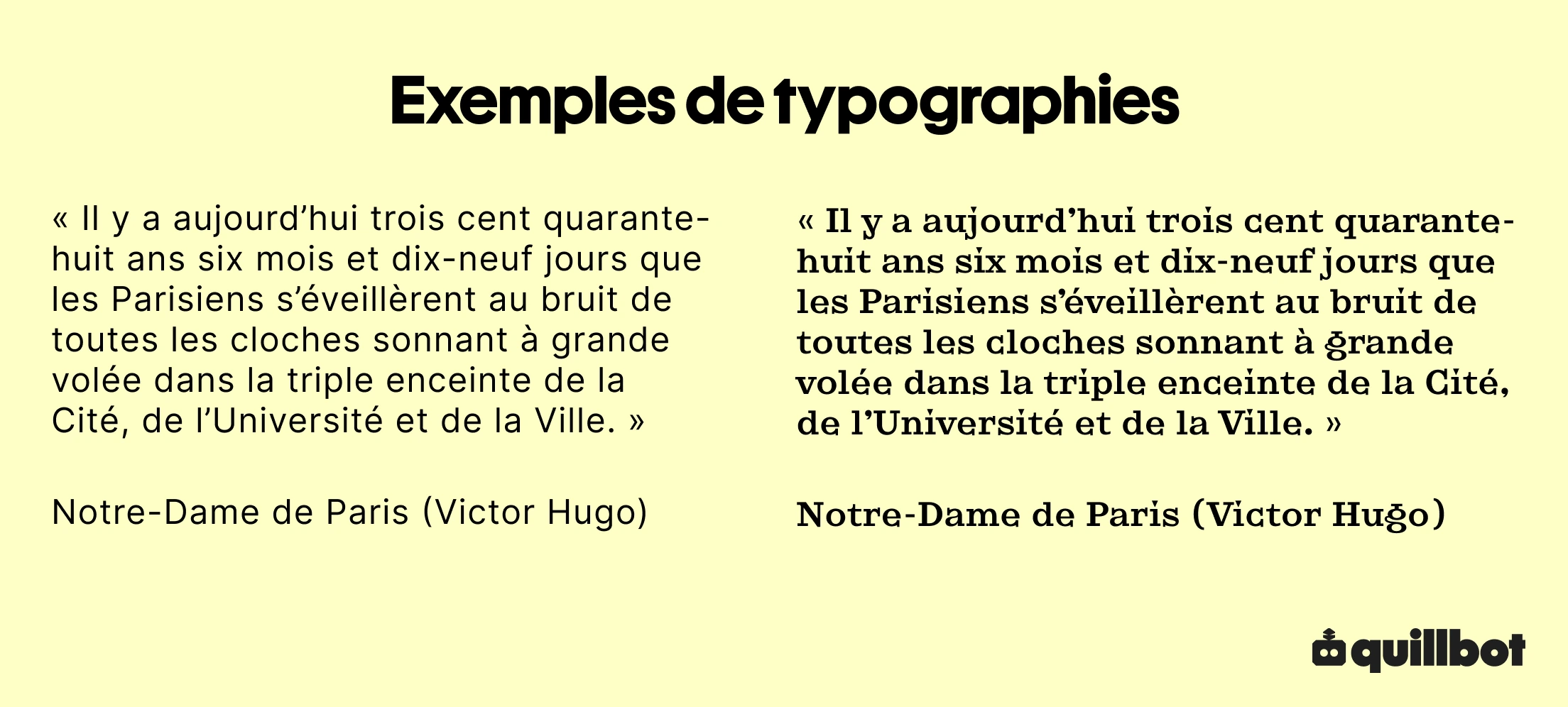
Choisir la bonne typographie | Explications
La typographie pare les lettres d’atours physiques et agence le texte selon une structure canonique. Elle est la clé de voûte d’un esthétisme textuel formel.
Lorsqu’elle est inadaptée, le texte perd bien plus que le sens du message ou la clarté du propos : il perd en crédibilité, et ce, avant même d’être lu.
Primordial, le choix d’une typographie qui captive le public relève d’une cohérence visuelle, qui, au-delà de l’esthétisme, aguiche l’œil du lecteur et séduit l’audience.
Choix typographique : la forme
Par sa forme, sa taille et sa couleur, une police typographique revêt chaque caractère d’un costume spécifique. Loin d’être anodine, cette apparence donne au lecteur une première impression du texte.
Toute personnelle et subjective qu’elle soit, cette première impression est une construction sociale. Les formes et les couleurs transmettent une émotion basée sur un héritage culturel partagé.
La typographie donne le ton d’un texte au premier coup d’œil parce que certaines structures influencent grandement notre jugement.
Bonne typographie
Les polices à empattements
L’empattement (ou serif) d’un caractère correspond à la petite extension à la tête ou au pied des lettres.
Les polices à empattements (comme Times New Roman, Garamond ou Baskerville) facilitent la lecture, mais transmettent également des valeurs d’autorité et de respectabilité.
De manière générale, les lignes droites et les angles de ces polices évoquent l’efficacité, la stabilité et tous les honneurs qui entourent une réputation bien établie.
Du document juridique à l’article universitaire, ces polices angulaires sont privilégiées par la presse traditionnelle et le monde de l’édition pour leur référence visuelle à l’imprimerie classique.
Bon à savoir…
La taille, la forme et l’aspect d’un caractère induisent également sa perception.
Plus le corps du caractère est gros et plus le texte est lisible, ce qui évoque la franchise, mais peut aussi se transformer en défaut : un lecteur âgé se sentira considéré, tandis qu’un lecteur plus jeune s’estimera infantilisé.
Le gras est un artifice typographique majeur, car il attire l’attention sur une information importante. Son abus brouille toutefois la hiérarchisation de l’information.
Au-delà de leur fonction, des traits épais ou fins expriment des notions différentes : la puissance ou la sophistication. L’italique, comme le gras, nécessite une utilisation parcimonieuse et équilibrée en fonction du contenu et de la structure du texte.
Le crénage d’un texte participe également de cette première impression. Un texte très aéré offre immédiatement une impression de calme et de sérénité, alors que des caractères trop resserrés affichent une forte densité, synonyme de tension.
Les polices sans empattements
Les polices sans empattement (ou sans-serif) sont dépouillées et minimalistes. Héritées de la révolution industrielle et liées au courant du modernisme, ces polices (Helvetica ou Futura) éliminent le superflu pour se concentrer uniquement sur la fonction du caractère.
Débarrassées de leurs fioritures, elles témoignent d’une transparence et d’une honnêteté qui écartent toute euphémisation ou infantilisation du message.
Cet aspect direct et sans détour réside également dans le contraste entre l’aspect des caractères. Tandis qu’une police droite exprime la neutralité, l’italique suggère le mouvement et l’urgence ; le gras ralentit la lecture et impose son poids.
Largement plébiscitées sur le web, ces polices font partie de toute communication numérique qui se veut innovante, moderne et tournée vers l’avenir.
Les polices manuscrites
Les polices manuscrites (ou scriptes) imitent l’écriture cursive, celle produite lorsqu’on écrit à la main. Parce qu’elles évoquent l’humain, elles font référence à sa créativité et à son authenticité.
Les courbes et les cercles que produisent les pleins et les déliés d’une plume chargée d’encre sont le gage d’une fabrication artisanale, unique et personnalisée.
Ces polices affichent également une certaine élégance à condition qu’elles ne nuisent pas à la lisibilité des caractères. Symbole de douceur, une typographie arrondie (Comfortaa ou VAG Rounded) doit rester non seulement facile à déchiffrer, mais surtout d’une lecture rapide et aisée.
De fait, la nostalgie que ces polices évoquent permet d’établir un véritable lien de proximité entre le texte et son lecteur.
Choix typographique : le public
Trop souvent oubliées, les notions d’accessibilité et de lisibilité doivent impérativement influencer le choix typographique.